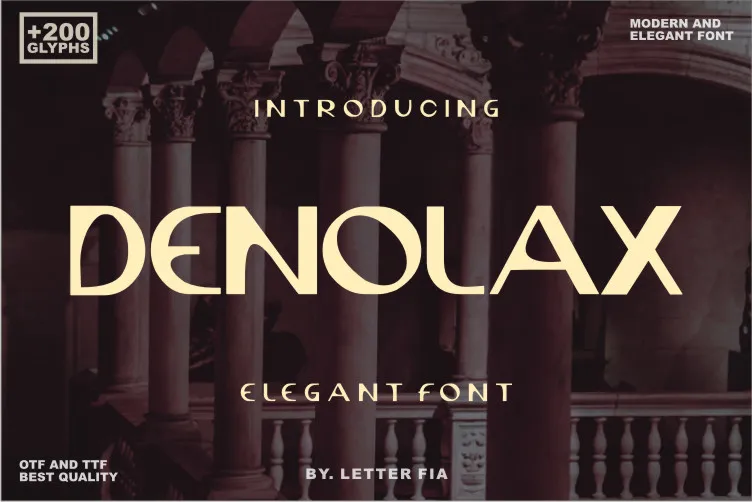
Denolax Font – Fonte Grátis
Denolax Font
Esta é uma fonte para exibição chamada Denolax Font criada pelo designer letterfiastudio. Esta família de fonts é perfeitamente adequada para diversas aplicações, como etiquetas de roupas customizadas, logotipos para marcas de esportes ou desportivas, e até mesmo anúncios que buscam se destacar. Com seu estilo elegante e distintivo, a Denolax Font traz um toque moderno e criativo às criações gráficas. Seja em roupas esportivas personalizadas, logos de marca ou anúncios no mundo da moda, este font oferece uma maneira única de destacar seus produtos e ideias. Esta família de fonts está disponível para aqueles que buscam complementar suas criações com um toque criativo e moderno. É perfeita tanto para designers profissionais quanto para iniciantes em busca de adicionar um toque único a seus projetos. Seja você uma marca jovem, um estilista visionário ou simplesmente alguém que deseja tornar seu projeto ainda mais chamativo com esta fonte, Denolax não só se encaixa perfeitamente, mas ajuda a transformar suas ideias em arte.